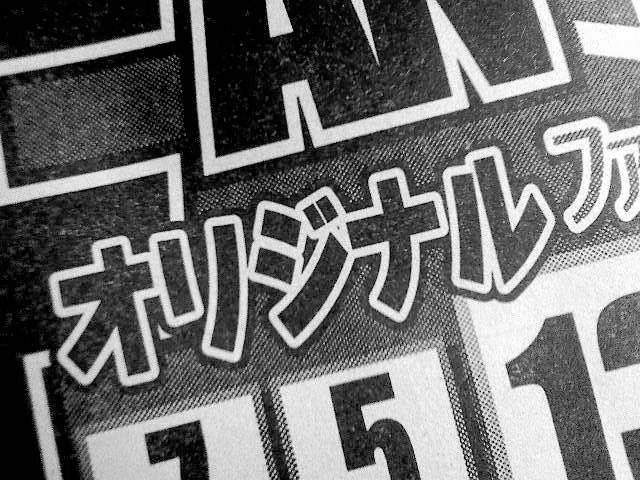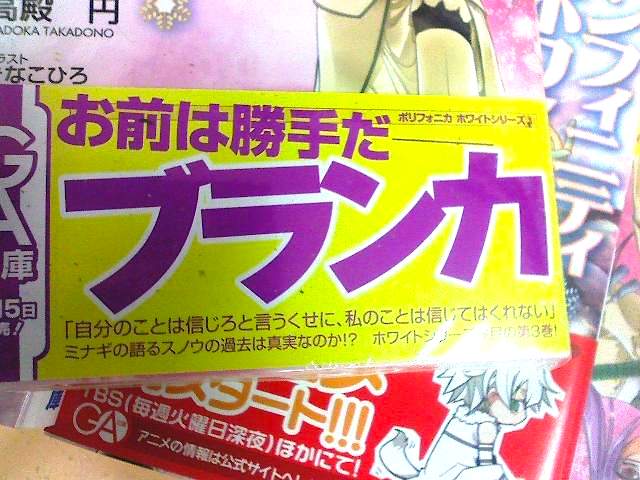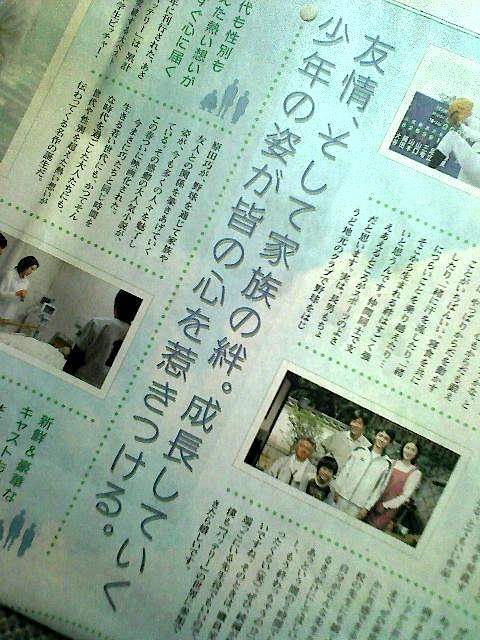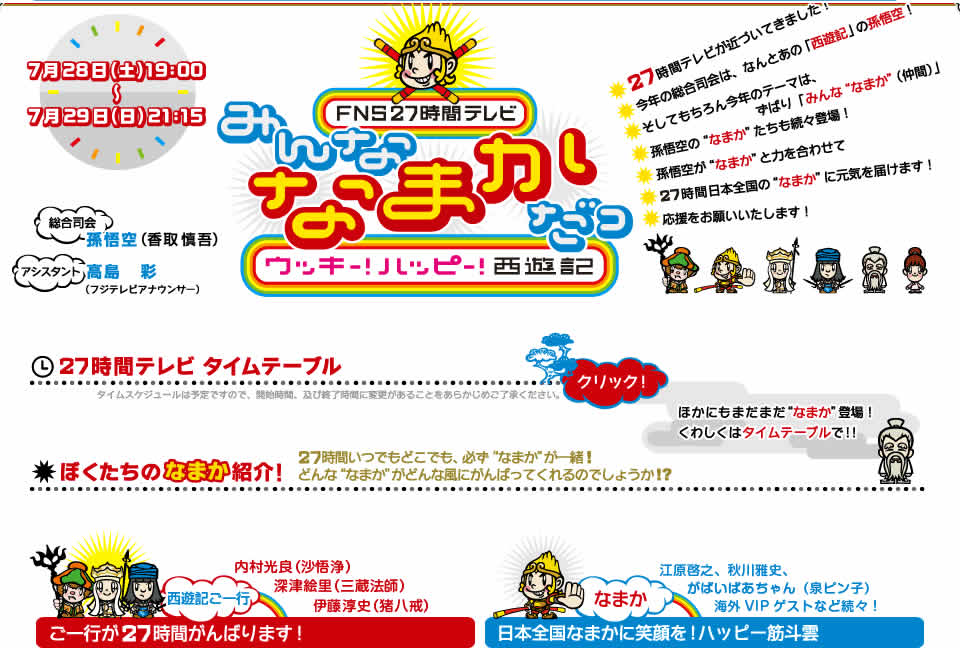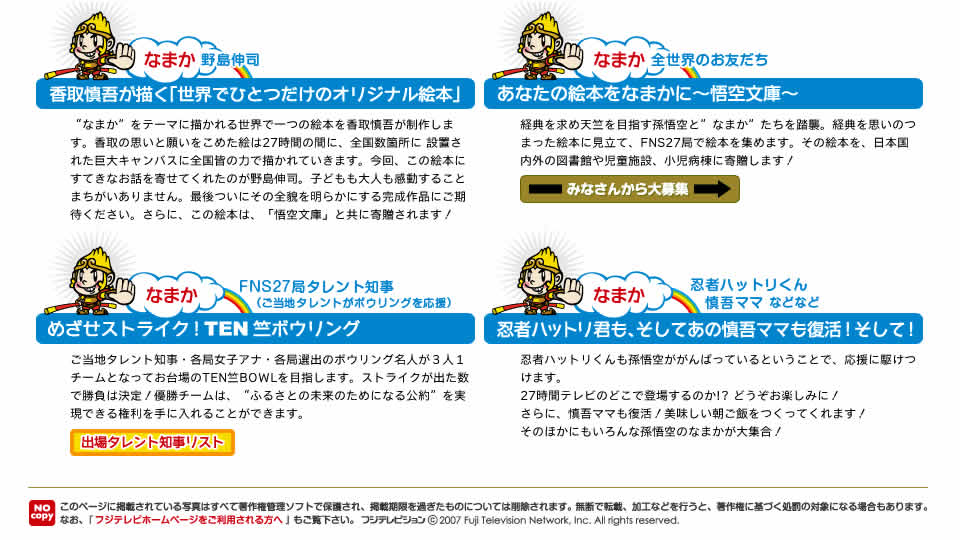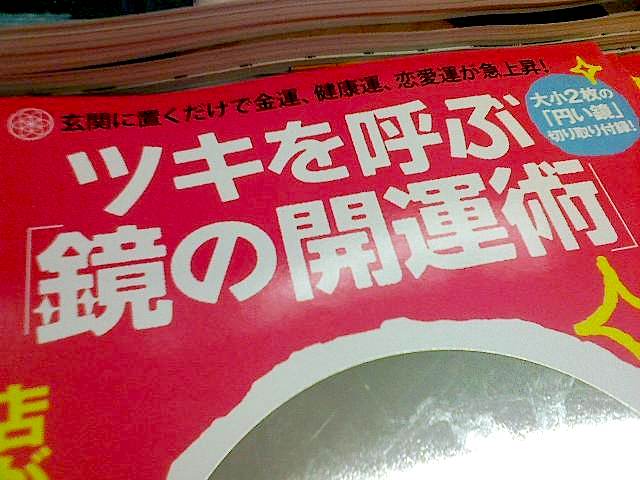
ケーブルテレビの宣伝 さとうゆたか
小さい文字もわんぱくですね。
あたしンち さとうゆたか
某新聞日曜版に連載されている人気漫画をまとめたもの。
写植文字盤時代の古いバージョンで一番太いもの。
1994年の1号目からずっと書名ロゴとして使われている。
けらえいこ、という著者名部分もわんぱく書体。
「ン」と「え」の点は、丸く加工されている。
あたしンち 交茶店
テレビでもずいぶんまえから放映されていますね。
しっかり目に入ります。
ダイエット本の表紙 さとうゆたか
書名:食べてやせる! 魔法のダイエット
細めのウェイトを使った理由は、ダイエット本だからでしょうか。
帯の書体もわんぱくです。
あかぽっぽ さとうゆたか
新聞広告 さとうゆたか
今朝の読売新聞全面広告。
本文中の小見出しにも「わんぱく」が使われていました。
バナナダイエット さとうゆたか
書名:朝バナナダイエット
書名のカタカナ部分だけですけど…
新聞広告 さとうゆたか
海外旅行の宣伝です。
雑誌の記事、扉ページ さとうゆたか
女性向けの雑誌だったかな…
映画の広告 さとうゆたか
新聞全面サイズのカラー広告です。
映画の題名は「ダイブ!!」。
泥だんごの作りかた さとうゆたか
こんな題名の本もあるんですね。
いろんな太さのわんぱく書体が使われています。
書 名:ピカピカ泥だんごの作りかた